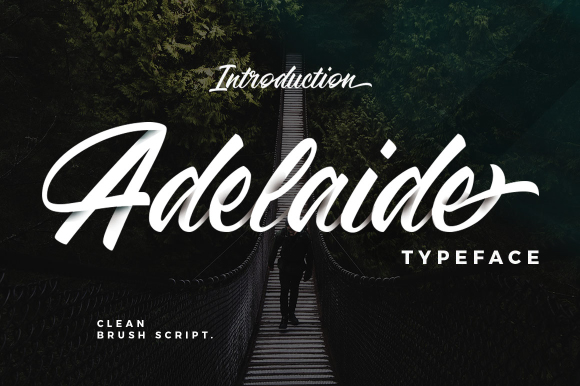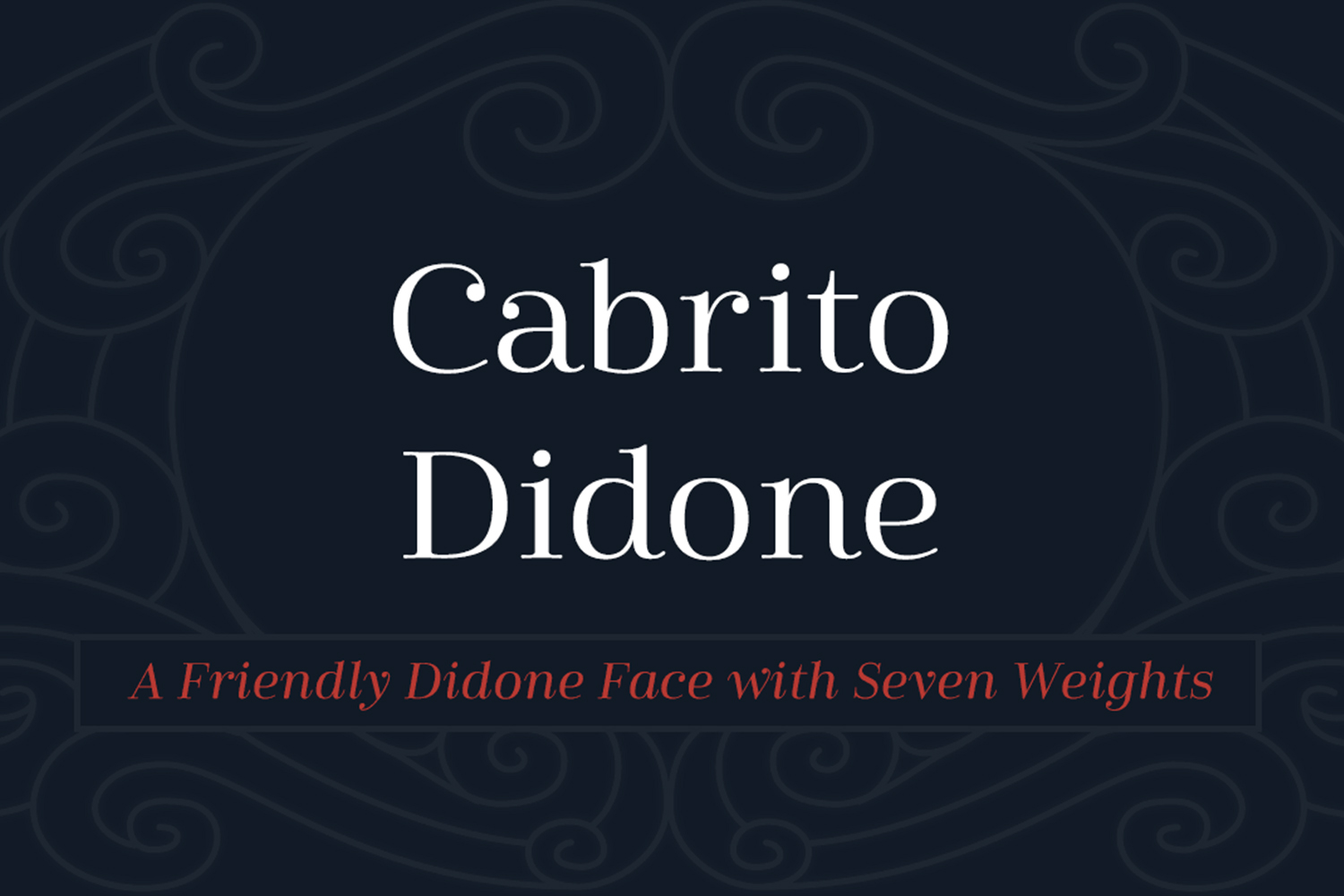
Top 14+ các font chữ design nổi tiếng cho người làm thiết kế
Font chữ design là một trong những yếu tố quan trọng không thể vắng mặt khi nhắc đến sự thành công của một bản thiết kế đồ họa. Đặc biệt, đối với các thiết kế yêu cầu tính thẩm mỹ cao. Chính vì vậy, trong khuôn khổ bài viết này, UNICA sẽ chia sẻ cho các bạn “chiếc chìa khóa vàng” để nâng tầm thiết kế của mình.
Manhattan
Manhattan là một font chữ Serif rất sang trọng. Đây chính là sự lựa chọn hoàn hảo khi kết hợp font chữ này với font chữ khác. Với nét chữ thanh mảnh, Manhattan không chỉ được sử dụng cho tiêu đề chính, tiêu đề phụ, mà còn được sử dụng để truyền tải thông điệp của công ty. Font chữ design là một font chữ bạn không nên bỏ qua cho thiết kế của mình.
Manhattan là một fonts chữ Serif rất sang trọng
Adelaide
Adelaide là một font chữ hoàn hảo, nó đáp ứng những yêu cầu mà người sử dụng mong muốn trong font chữ Serif. Người ta thường nhìn thấy sự bóng bẩy của font chữ này qua sự chuyển đổi giữa nét thanh và nét đậm trong cùng một chữ cái, chúng được trình bày một cách nhẹ nhàng, uyển chuyển. Chính vì lý do này mà nó thường được sử dụng rộng rãi trong thiết kế bao bì, thiết kế Logo, thậm chí là cho thiết kế web.
Elaris
Với dân thiết kế đồ họa thì font chữ Elaris không phải là cái tên xa lạ rồi đúng không nào. Elaris mang đến một sự thay đổi đầy thú vị cho các font chữ Serif thông thường. Với các chủ đề về thiết kế thời trang và lối sống thì Elaris chính là sự lựa chọn không thể tuyệt vời hơn. Khi sử dụng font chữ này nó sẽ mang đến vẻ đẹp thanh lịch cuốn hút người xem ngay từ cái nhìn đầu tiên.
font chữ Elaris
Marschel
Marschel là một font chữ mang hơi hướng lãng mạn vào kiểu chữ Serif truyền thống với các đường cong thanh nhã. Đây là font chữ được lấy cảm hứng từ La Mã. Ngoài việc sử dụng cho các tiêu đề, Marschel còn được sử dụng trong thiết kế Logo, cùng các yếu tố khác của thương hiệu.
Font chữ Marschel
Leyton
Khi bạn nhìn vào font chữ Leyton, chắc chắn bạn sẽ bị nó cuốn hút chỉ trong vài giây đầu tiên bởi vẻ đẹp quyến rũ đan xen với sự độc đáo của nó. Đây là font chữ theo phong cách hiện đại so với các font chữ Serif khác. Do đó mà nó trở thành một font chữ hoàn hảo để sử dụng cho tiêu đề chính, tiêu đề phụ, hoặc bất kỳ yếu tố nào trong bản thiết kế cao cấp.
Leyton là font chữ theo phong cách hiện đại so với các font chữ Serif khác
Cabrito Didone
Cabrito Didone mang đến cho người xem một vẻ ngoài vui nhộn với các đường cong lạ mắt. Tuy nhiên, nó vẫn toát lên một vẻ quý phái riêng của nó mà không thể lẫn vào đâu được. Và đây chính là điểm nhấn tuyệt hảo cho các thiết kế cao cấp hoặc các bài viết về chủ đề thời trang, lối sống.
Zimra Serif
Nếu bạn muốn một font chữ sang trọng thì Zimra sẽ đáp ứng mọi yêu cầu của bạn. Bởi font chữ này mang lại sự duyên dáng, thanh lịch ngay cả khi nó được trình bày một cách đơn giản trên một nền tảng.
Halminton Grand
Halminton Grand không chỉ là một Font chữ design mà nó còn mang trong mình vẻ mềm mại, quý phái đến kỳ lạ. Font chữ này thường được lựa chọn khi xây dựng thương hiệu, các bảng hiệu quảng cáo và các bản thiết kế đòi hỏi sự sang trọng. Dễ hiểu vì sao mà Halminton Grand lại được nhiều người lựa chọn đến vậy.
Font Halminton Grand
Benjamin Title Typeface
Font chữ này không chỉ mang đến kiểu dáng của một font chữ Serif truyền thống mà nó còn khoác lên mình một tính cách hiện đại và độc đáo. Benjamin Title Typeface thể hiện được sự đẳng cấp và cả sự tự tin với các đường nét đậm, phù hợp với mọi thiết kế đòi hỏi tính chuyên nghiệp.
Ravensara sans
Đây là font chữ pha trộn giữa các đường kẻ mỏng và dày một cách liền mạch. Yếu tố này tạo cho Ravensara sans một vẻ thanh lịch đặc biệt. Đây chính là sự lựa chọn hoàn hảo cho các hãng thời trang cao cấp khi dùng trong thiết kế thương hiệu và bao bì sản phẩm.
Metropolis
Metropolis là một font chữ được lấy cảm hứng từ thành phố. Với kiểu dáng hiện đại và bắt mắt, nên nó chính là cái tên không thể bỏ qua cho các tác phẩm kinh điển với một cái nhìn hiện đại, thể hiện sự đẳng cấp của người thiết kế chuyên nghiệp.
Metropolis là một font chữ được lấy cảm hứng từ thành phố
Kết luận